「ヒラギノフォント」をご存知ですか? 世の中で一番有名で身近なフォントかもしれない、ヒラギノフォントのルーツを探る。SCREENグラフィックソリューションズのフォントの世界。
SCREENグラフィックソリューションズ
皆さんは、SCREENグラフィックソリューションズというフォントメーカー、ご存じでしょうか? SCREENと聞くと、大日本スクリーン製造という社名が頭に浮んだ人が多いのではないでしょうか。半導体・液晶製造装置・印刷関連機器などの産業用機器を製造する世界的に有名な大企業です。本社は京都にあります。2014年に持株会社体制移行にともない、社名がSCREENホールディングスに変更になりました。
SCREENホールディングスのグループ企業の中で、印刷関連機器事業を担う会社が、SCREENグラフィックソリューションズになります。印刷関連機器において、フォントは欠かせない存在です。
「ヒラギノ」というフォント名を聞いたことがない人にとっても、実は、毎日の生活の中で身近な存在であり、必ず目にしたことのある書体なのです。ヒラギノフォントは、iPhoneやmacOSに標準フォントとして搭載され、高速道路のサインシステムなどでも使用されているとても有名な書体です。
そして、その書体を提供しているフォントメーカーが、SCREENグラフィックソリューションズという会社なのです。この記事の中では、以下、「SCREEN」と略して表現します。
「ヒラギノ角ゴ」と「ヒラギノ明朝」
グラフィックデザインやウェブ制作に関わる人であれば、「ヒラギノ角ゴ(ヒラギノ角ゴシック体)」と「ヒラギノ明朝(ヒラギノ明朝体)」を知らない人はいないと思います。ちなみに、「角ゴ」は「カクゴ」と読みます。
それでは、まずは「ヒラギノ角ゴ」と「ヒラギノ明朝」をFONTPLUSのためし書きで表現してみましょう。
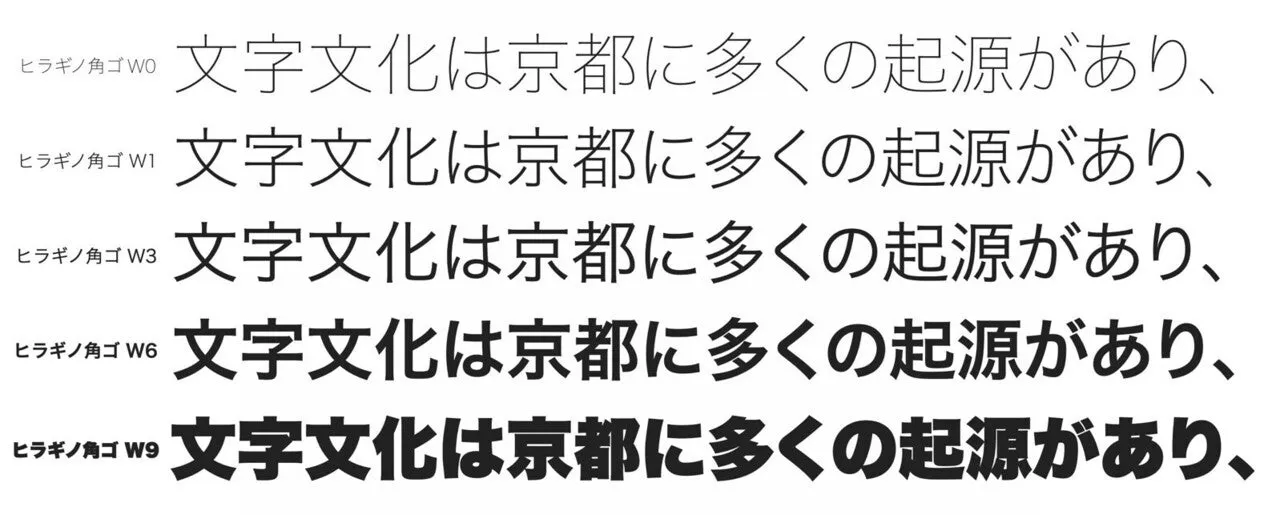
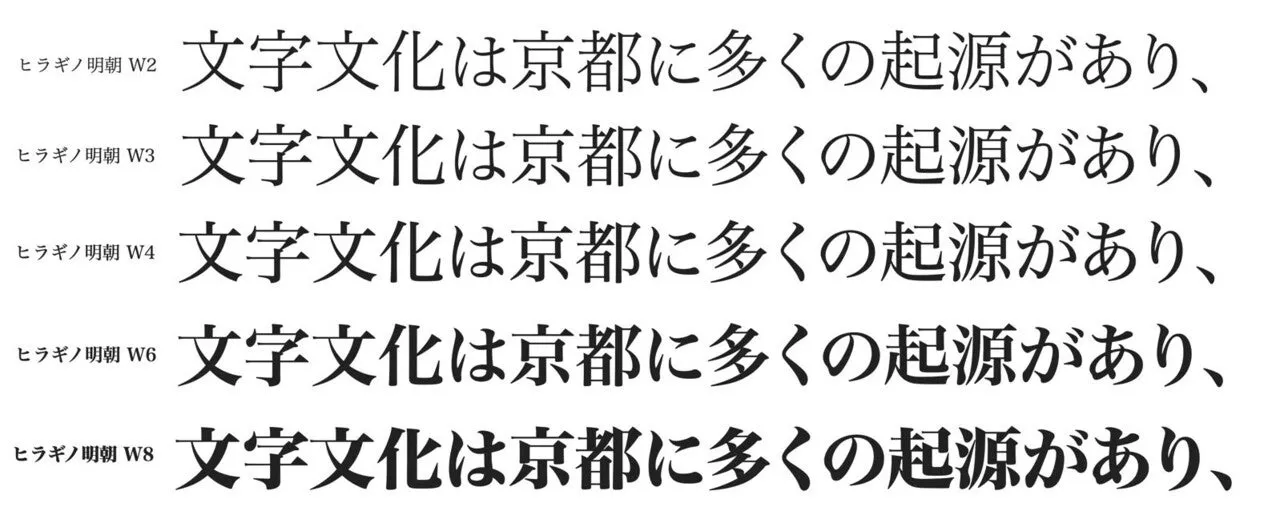
美しくて読みやすい書体です。日本にiPhoneが初登場したのが2007年なので、iPhoneを使用するようになってから14年が経過しました。日本ではiPhoneを使用している人が多いので、14年間、多くの日本人が無意識のうちに「ヒラギノ角ゴ」に毎日、接していることになります。
SCREENから提供されている「ヒラギノ角ゴ」には「W0」から「W9」までの10ウエイトがあります。同じフォントでも10種類のウエイト(文字の太さ)を持つファミリーは、文章表現をする上でとても役に立ちます。FONTPLUSでは、ヒラギノ角ゴは10ウエイト利用できます。
例えば、大見出し・小見出し・本文を文字サイズで変化を持たせて読みやすくする方法がありますが、同じ文字の大きさでウエイトを3種類(例えばW6、W3、W0)使うことで、情報の重み付けに変化を持たせることもできます。この考え方は、Webフォントを使うウェブサイトの文章表現だけでなく、ビジネス文章でも役にたつ表現方法です。
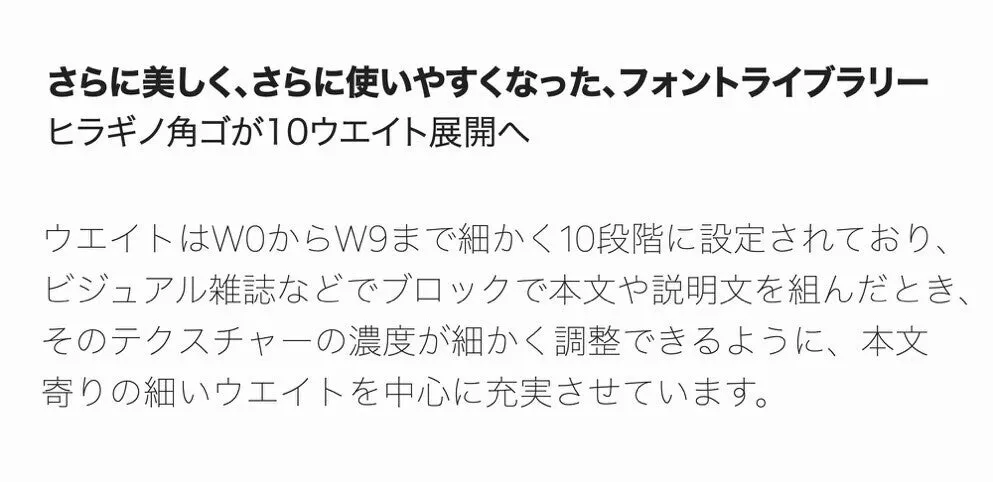
ヒラギノフォントのルーツを探る
ヒラギノフォントはいつ誕生したのか、名前の由来は何なのか、ルーツを探っていきましょう。
ヒラギノフォントは1990年に、大日本スクリーン製造(現在のSCREENグラフィックソリューションズ)が開発に着手したデジタルフォントです。今から約30年前に開発プロジェクトがスタートしました。
1990年といえば、米国が発祥の地であるDTP(デスクトップパブリッシング)が日本でも根付いてきた頃です。写真製版の総合機器メーカーであるSCREENは、従来の印刷製版設備に依存しないオープンな環境で利用できるデジタルフォントが必要になると考え、「デジタル時代のスタンダード書体」を目指してオリジナルフォントの開発に着手します。
書体開発にあたり、これから50年、100年使われるくせのないベーシックな書体スタイルであること、かつ、現代的で若々しいクールなイメージの書体であることをコンセプトとし、なんども試作開発し、チュー二ングを繰り返したとお聞きしました。1993年に「ヒラギノ明朝体」が発売され、1994年に「ヒラギノ角ゴシック体」、1996年に「ヒラギノ行書体」が誕生しました。
そして、2000年の幕張メッセで開催されたMACWORD Expo/Tokyoでのスティーブ・ジョブスの基調講演で、Mac OS Xへ「ヒラギノ明朝体 W3/W6」「ヒラギノ角ゴシック体 W3/W6/W8」「ヒラギノ丸ゴシック体 W4」の標準搭載が発表され、大きなニュースになりました。その後、2007年のiPhoneの日本発売において、iOSにヒラギノフォントが搭載されました。
一般ユーザーが簡単に入手できるiPhoneやMacBookにヒラギノフォントがシステムフォントとして標準搭載されていることは、今となっては当たり前のことのように感じますが、今から約20年前、MacのパーソナルコンピュータのOSにヒラギノフォントが使えることは衝撃的なことだったのです。DTP用のプロフェショナル書体が身近な存在になったのです。
活版印刷の歴史と比較すると、デジタルフォントの歴史はまだ始まったばかりです。「2000年にアップル社のヒラギノフォント標準搭載の出来事は日本語デジタルフォントの歴史を動かした」と、将来、歴史を語る日も近いと思います。
そんなムーブメントがきっかけとなり、2021年現在、macOSには、ものすごく沢山のプロフェッショナル向け日本語フォントが標準搭載され、Windows OSにも多くの日本語フォントが標準搭載される時代になりました。
ヒラギノという名前の由来
ヒラギノフォントの「ヒラギノ」の名前の由来について聞いてみました。
京都の地名から命名しました。フォント名やOSの名称に、地名を採用することはよくありますよね。「San Francisco」「Osaka」などは良い例です。新しい書体を開発していた頃、京都の地名をいろいろ集めて検討しました。様々な候補の中で「柊野(ヒラギノ)」という響きが、現代的で若々しいクールなイメージに合っていたため、「ヒラギノ」に決定しました。
毎日のように接しているヒラギノフォントの名前のルーツが京都の地名「柊野」だということ、フォント豆知識として覚えておくといいかもしれませんね。
文字の読みやすさの考察
ヒラギノフォントは、高速道路の標識で採用されていることでも有名です。
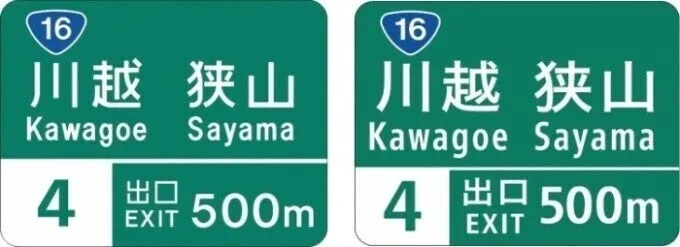
読みやすさとスタンダードさが特徴のヒラギノフォントにはどんな特徴があるのか聞いてみました。
線同士の空間を均一にしています。下記の挿絵で説明すると、丸の部分に一定の空間が確保されていることがわかると思います。線と線のあいだの空きが視覚的に均一に見えるようにしているということです。文字が小さくてもつぶれにくく、ヌケの良い明るい印象を与えます。組んだ時には、テキストブロックとしてグレートーンに統一感が生まれ、レイアウトデザイン全体にまとまりを与える効果もあります。
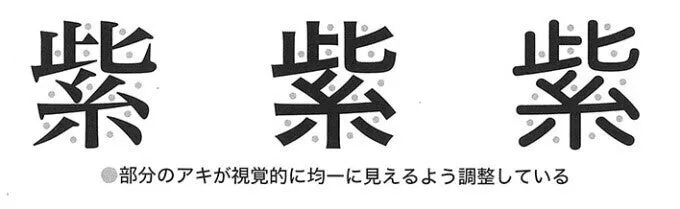
文字スタイルの違いにフトコロ(画と画により生まれる空間)という概念があります。フトコロが狭い書体や広い書体がありますが、ヒラギノフォントは中間を取り、文字のつぶれを防ぎ認識しやすいようデザインしています。
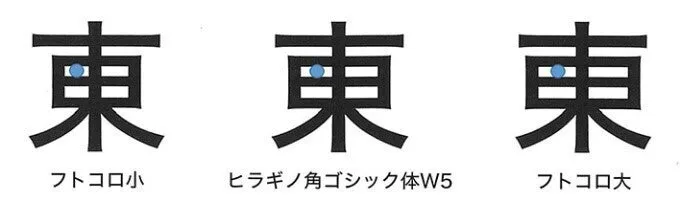
そして、文字の重心の位置も中間です。重心が高いとクラシックな印象になり、重心が低いと幼い印象になります。ヒラギノフォントはちょうどいい中間の位置に重心がくるようにデザインされています。
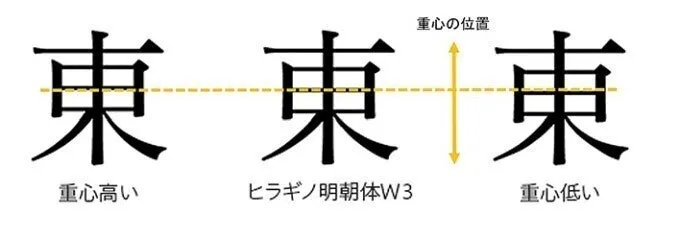
ヒラギノフォントの世界
SCREENからリリースされている代表的なフォントを、FONTPLUSためし書きで表現してみました。
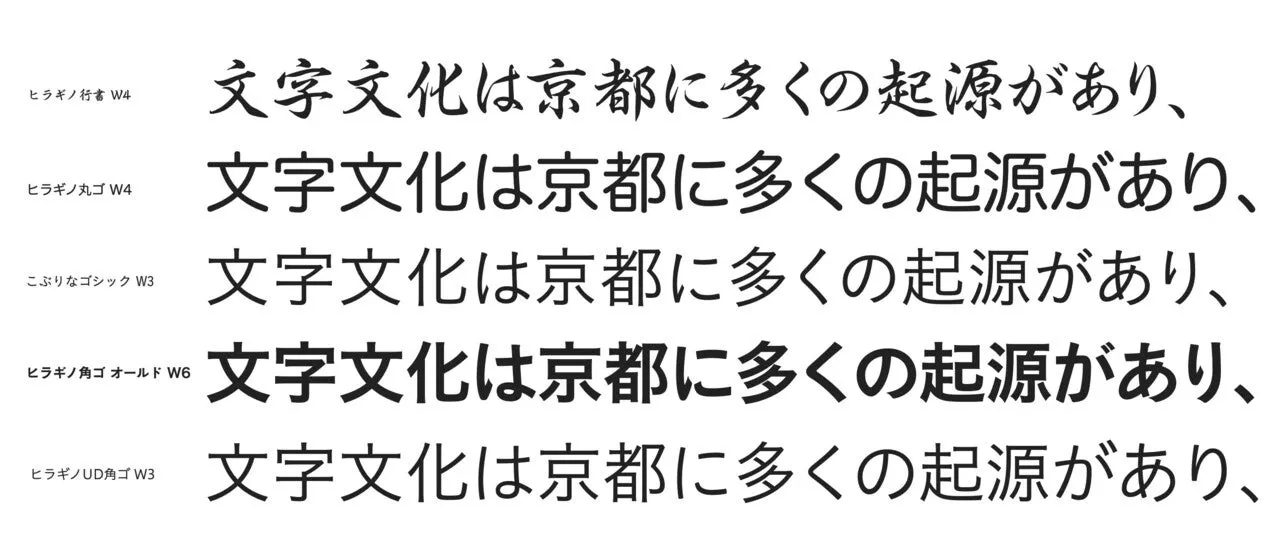
ヒラギノ角ゴシック体とヒラギノ明朝体が有名ですが、「ヒラギノUD角ゴ」「ヒラギノUD明朝」「ヒラギノ丸ゴ」「ヒラギノUD丸ゴ」「こぶりなゴシック」「ヒラギノ角ゴオールド」「ヒラギノ行書」などがあります。
ヒラギノフォントのどの書体も、スタンダートでベーシックなスタイルであり、現代的で若々しくてクールという共有点があると思います。さらには、ユニバーサルデザイン書体のバリエーションの選択もできるので、コンテキストにあわせてフォントの適材適所に対応できそうです。
また、ヒラギノフォントは、中国語(簡体・繁体)に積極的な展開をおこなっています。日本語のヒラギノ角ゴシックのデザインを忠実に踏襲した簡体中文・繁体中文は、中国市場にも進出しているグローバル展開する企業においても好評です。
現在、FONTPLUSでは、ヒラギノ角ゴの簡体中文と繁体中文、それぞれ2ウエイト(W3/W6)提供していますが、近日、ヒラギノ角ゴ簡体中文 Stdにおいて5ウエイトを追加リリースし、7ウエイト展開(W0からW6)でご利用できるよう準備中です。ご期待ください。FONTPLUSで使用できるヒラギノのWebフォントは、現在、55書体。近日、ヒラギノ角ゴ簡体中文Std において5書体追加し、60書体になる予定です。
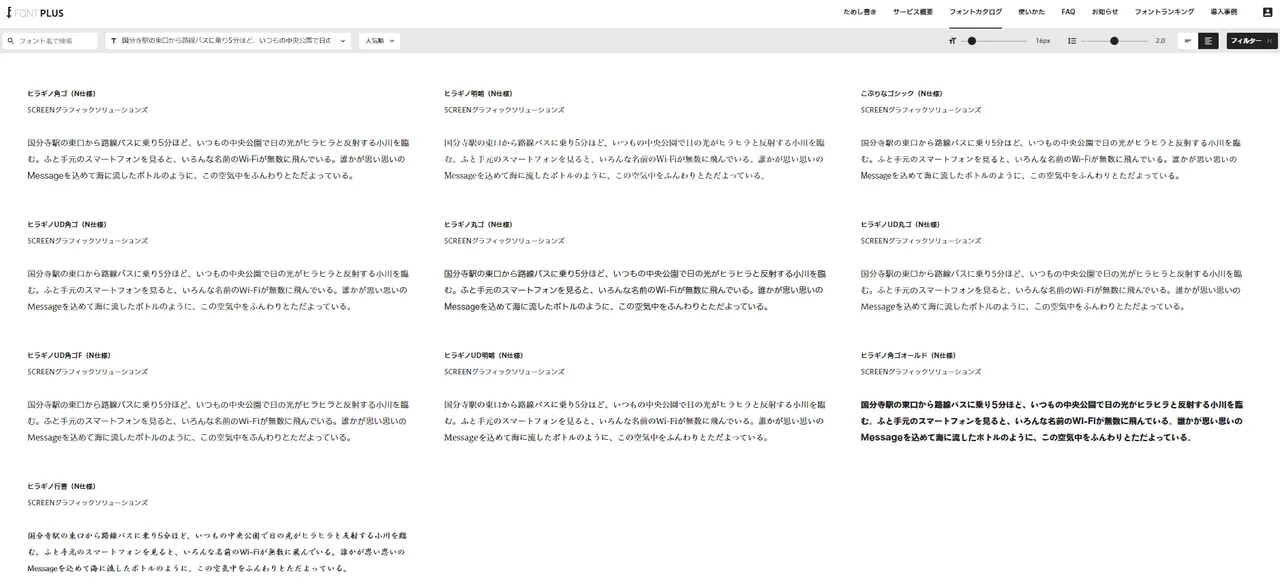
ヒラギノフォントを活用した導入事例
Webフォントとしてヒラギノフォントを活用した導入事例を2つ紹介します。「こぶりな」書体や「ヒラギノUD角ゴ」書体が、読みやすく美しいWebサイトの演出をさりげなく支えているのがとても印象的です。
サン・アドでは、見出しやナビゲーションで「こぶりな」書体が活用され、アクセントとしてのテキストがさりげなく上品です。縦書き・横書きレイアウトをうまく活用することで、美しいグラフィックデザインの作品集を読んでいる気分になります。
キヤノン グローバルでは、読みやすさを配慮したユニバーサルデザイン書体「ヒラギノUD角ゴ」書体が活用されています。企業ビジョン、会社情報、CSR活動などが掲載されたコーポレートサイトとしてのさまざまなコンテンツがさりげなく読みやすいです。全面的にWebフォントを採用しているにも関わらず、Webパフォーマンスに優れている点も印象的です。